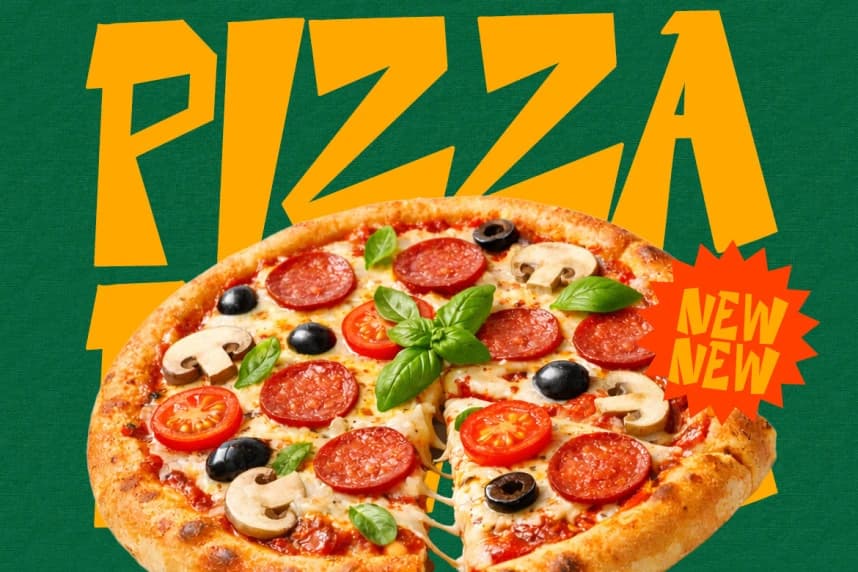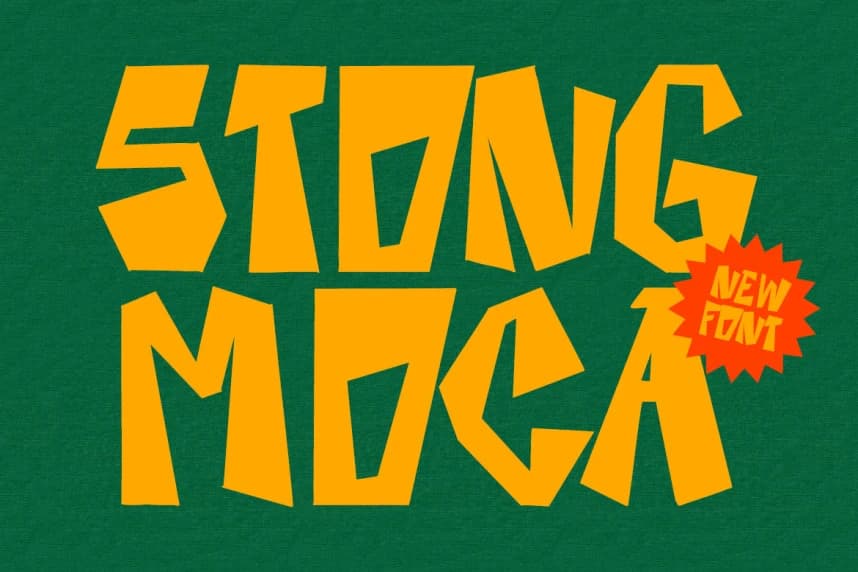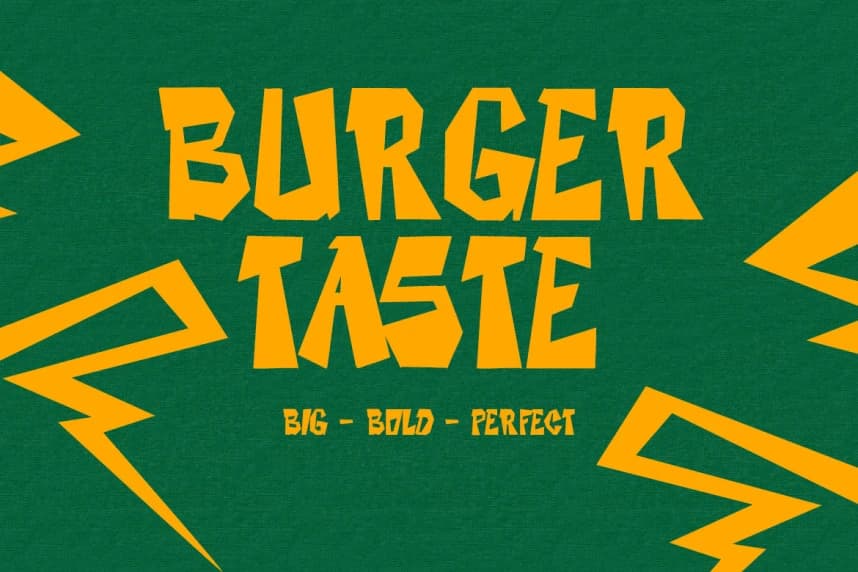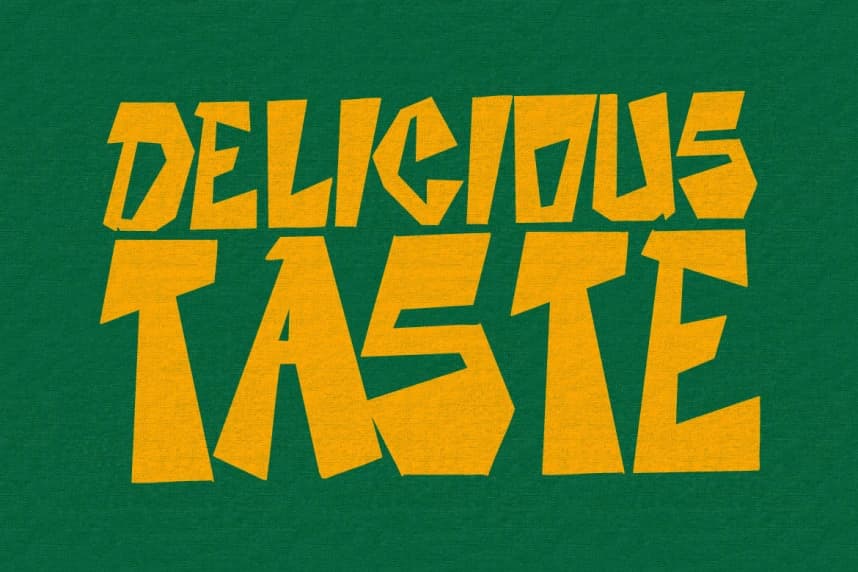
Stong Moca Font - Bu font, ağır ve düzensiz harf biçimlerine sahip olup keskin, dişli kenarlara sahiptir ve el kesimi ya da ilkel bir estetiği çağrıştırır. Çizgiler sağlam ve kalındır.
Stong Moca Font - Bu yazı tipi ağır, düzensiz harf biçimlerine sahip olup keskin, dişli kenarlarıyla el ile kesilmiş ya da ilkel bir estetiği çağrıştırır. Çizgiler sağlam ve kalındır.